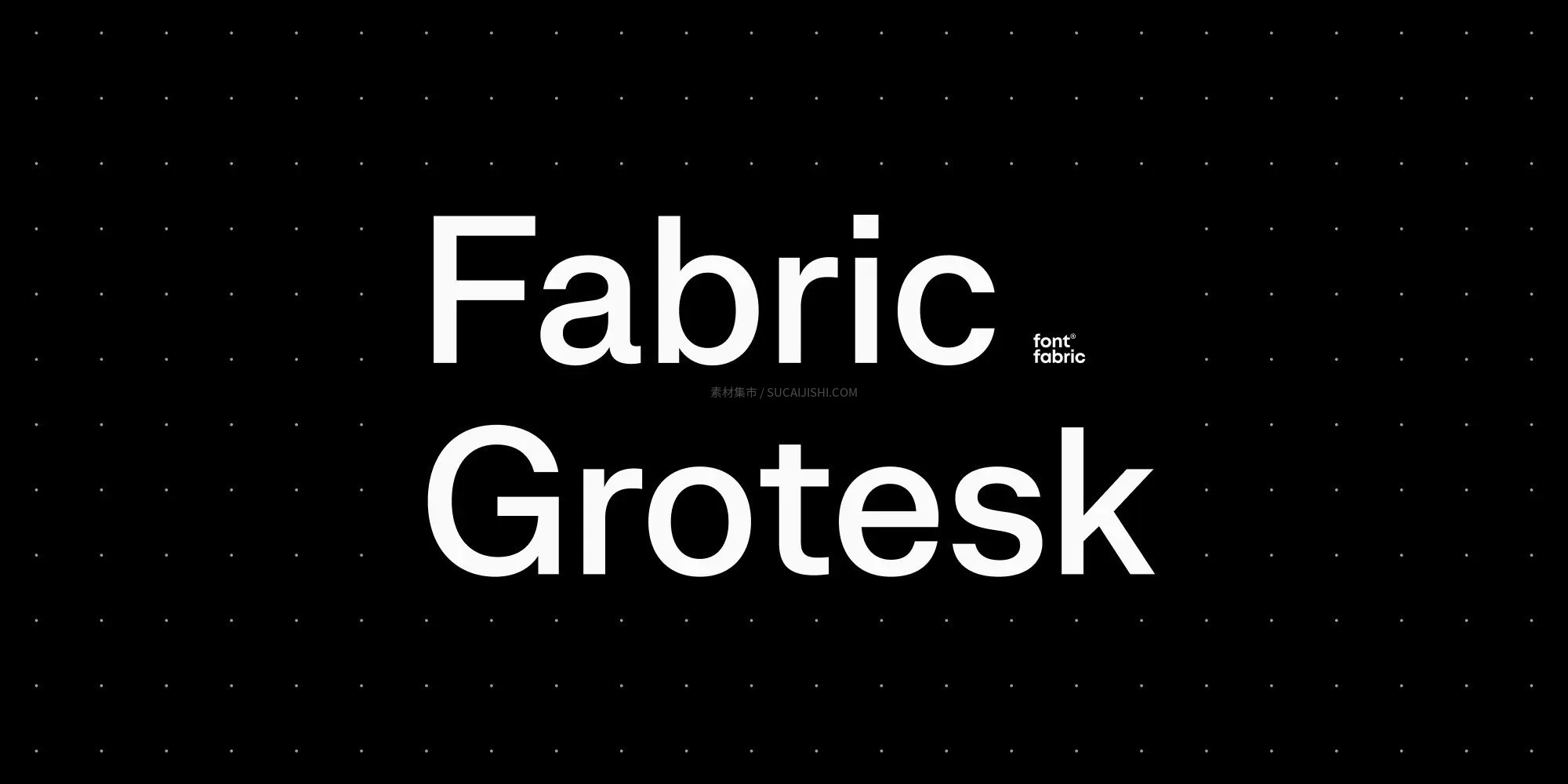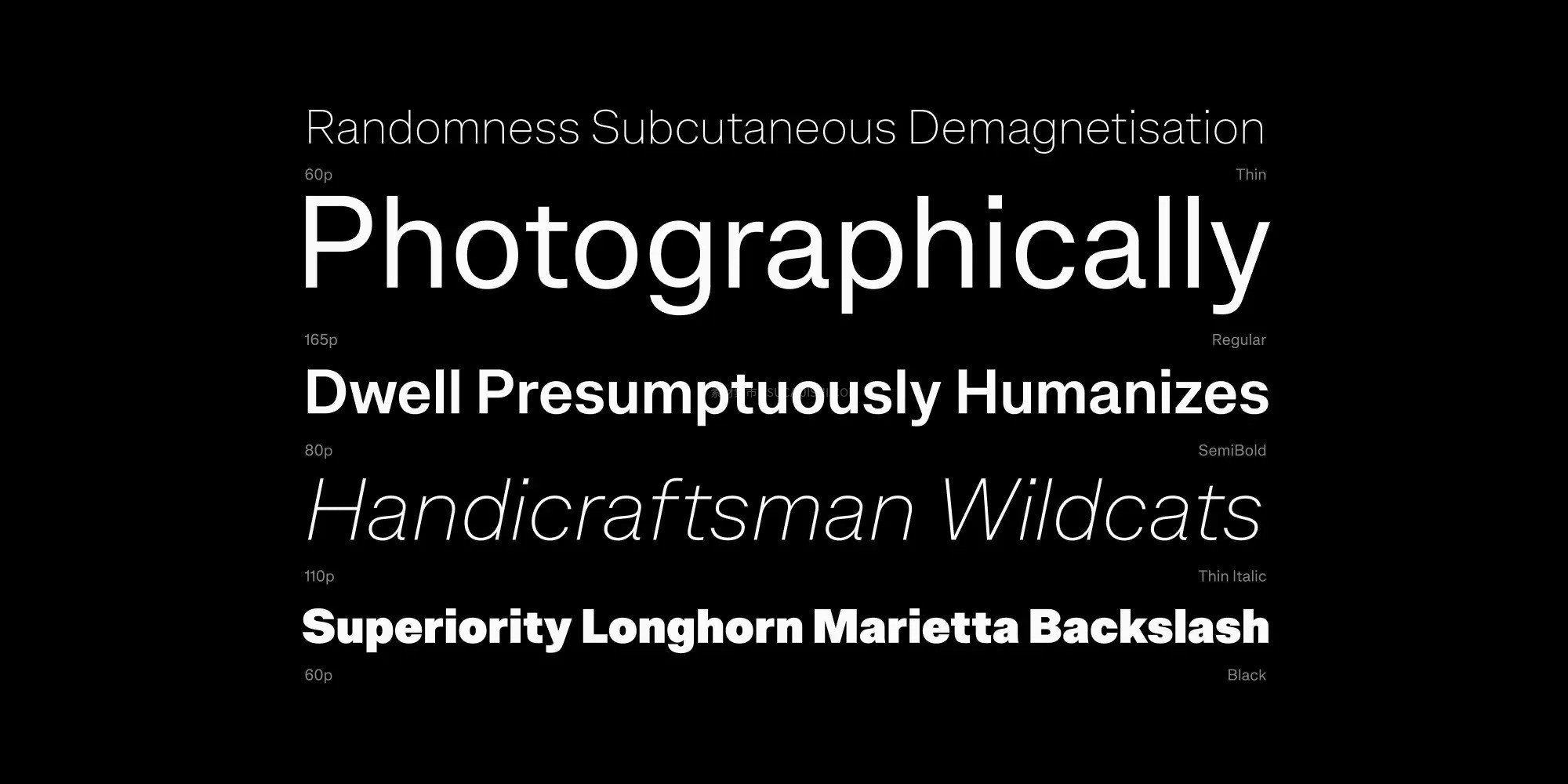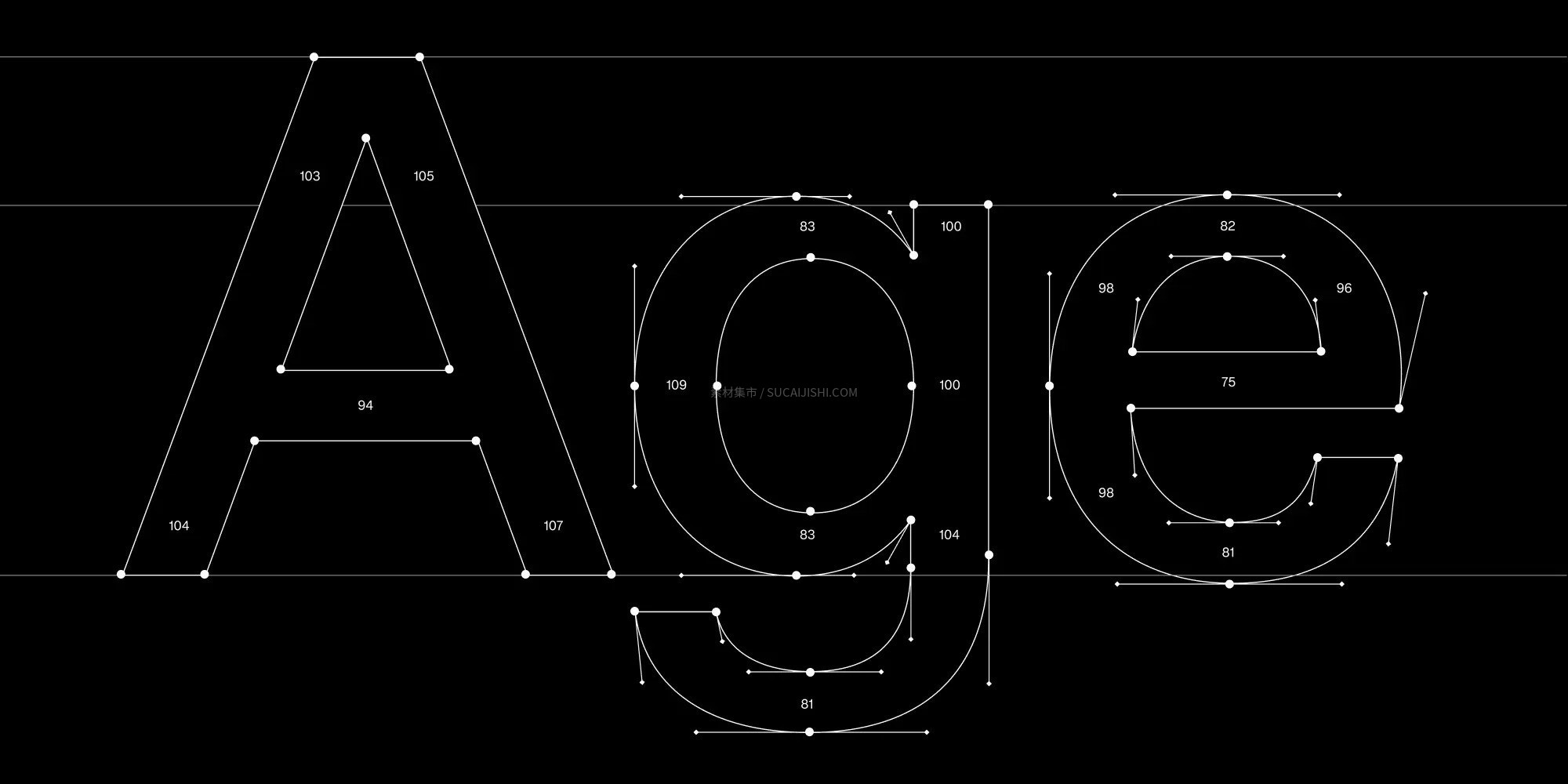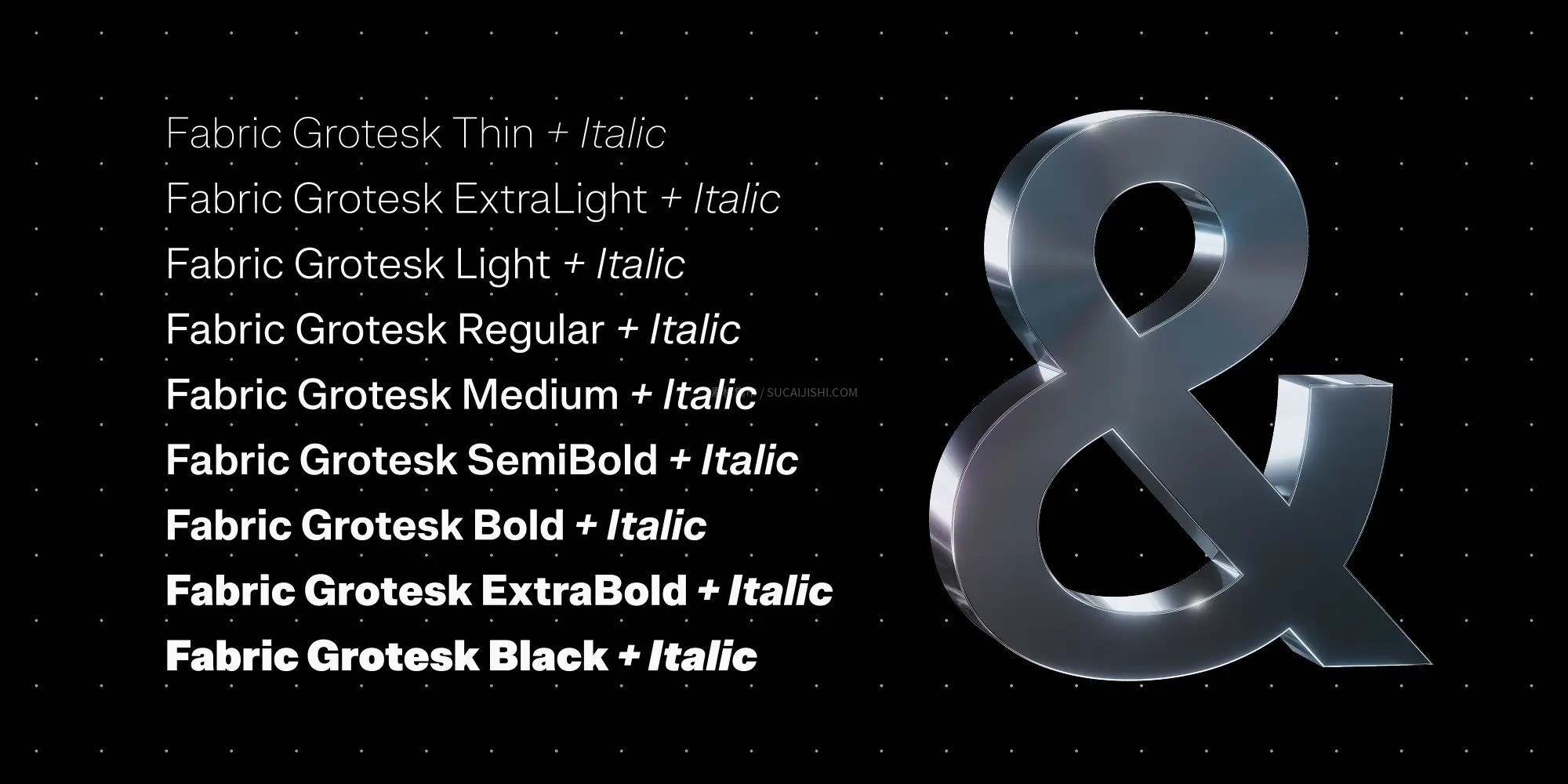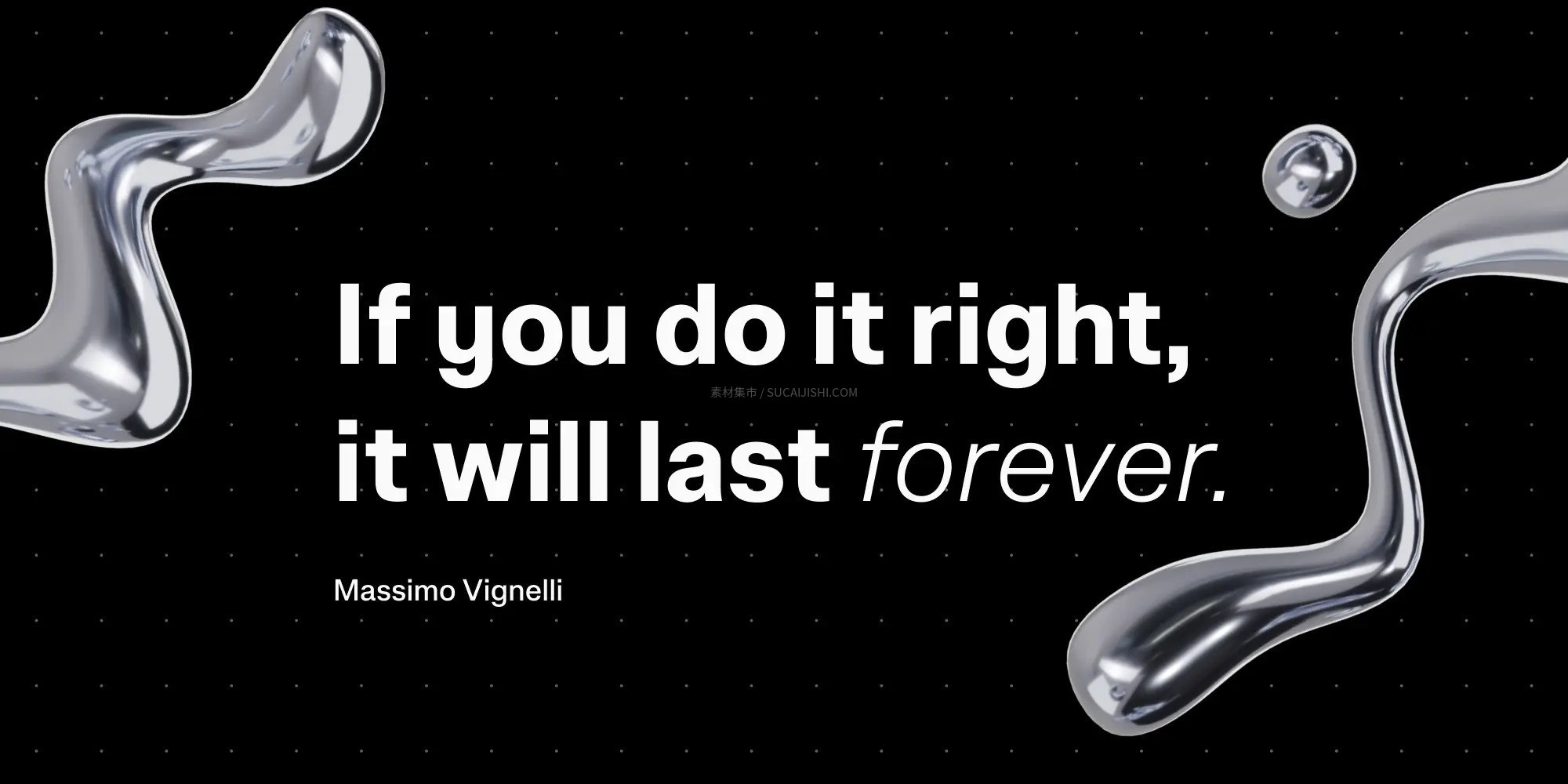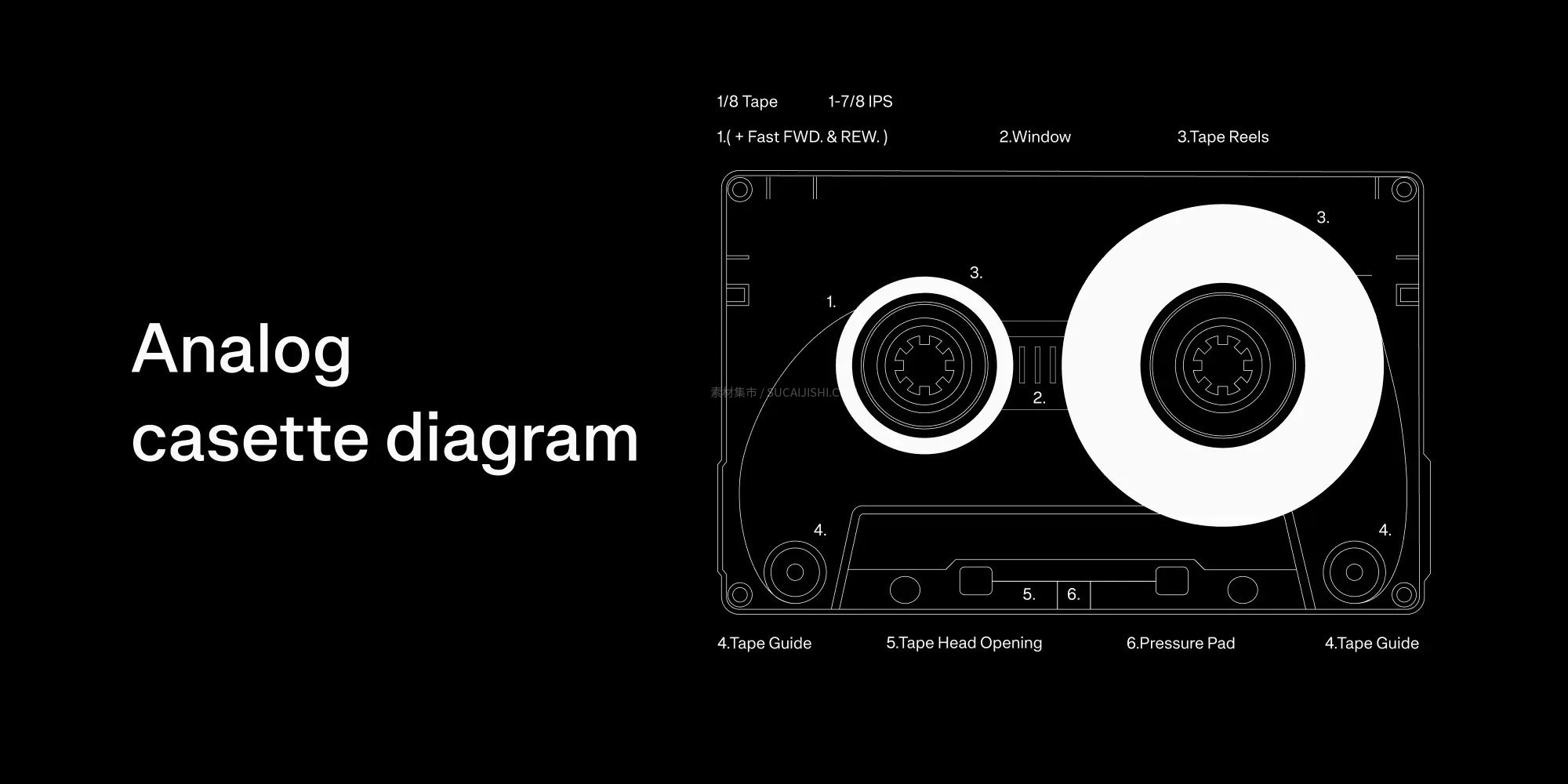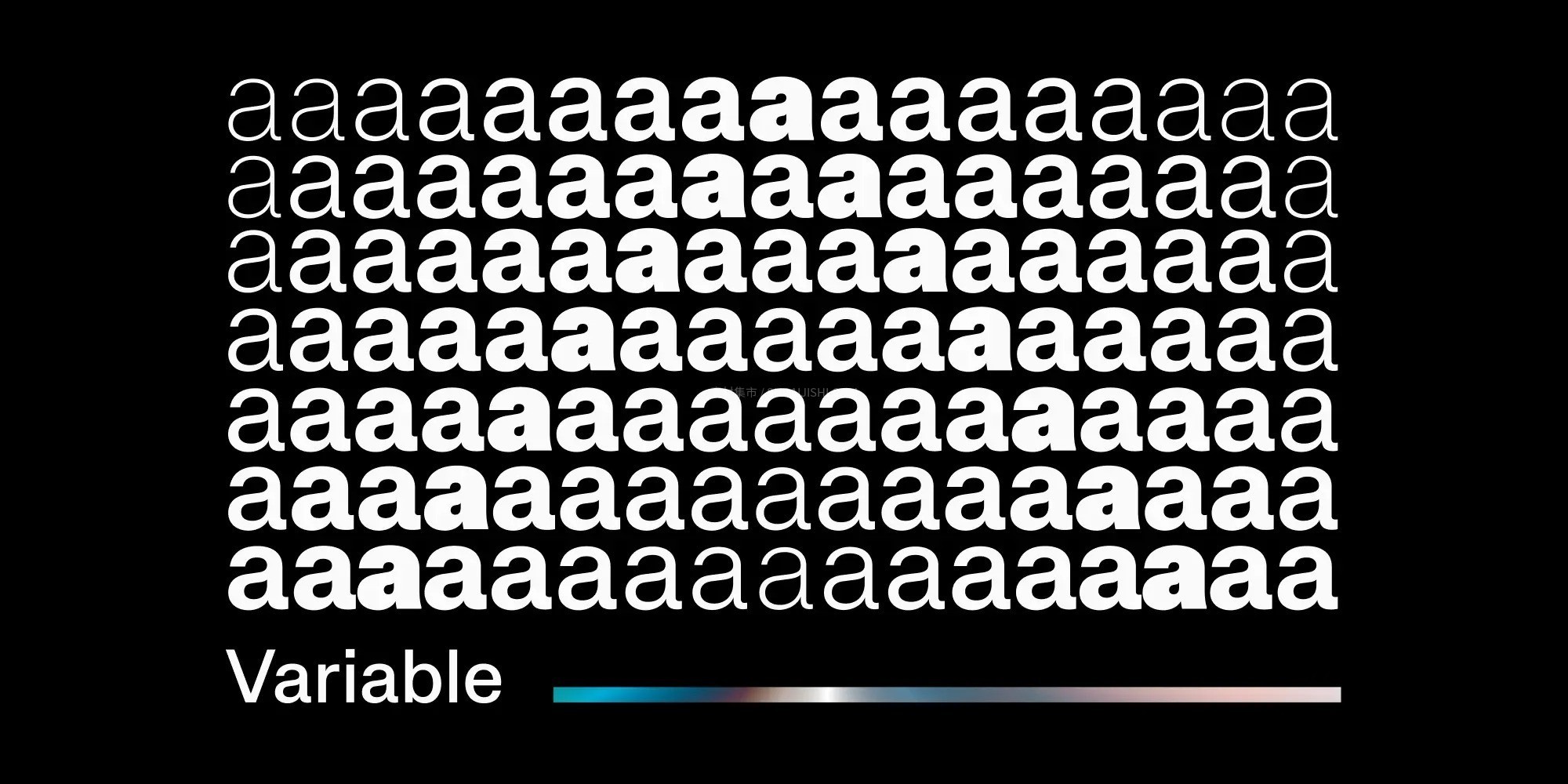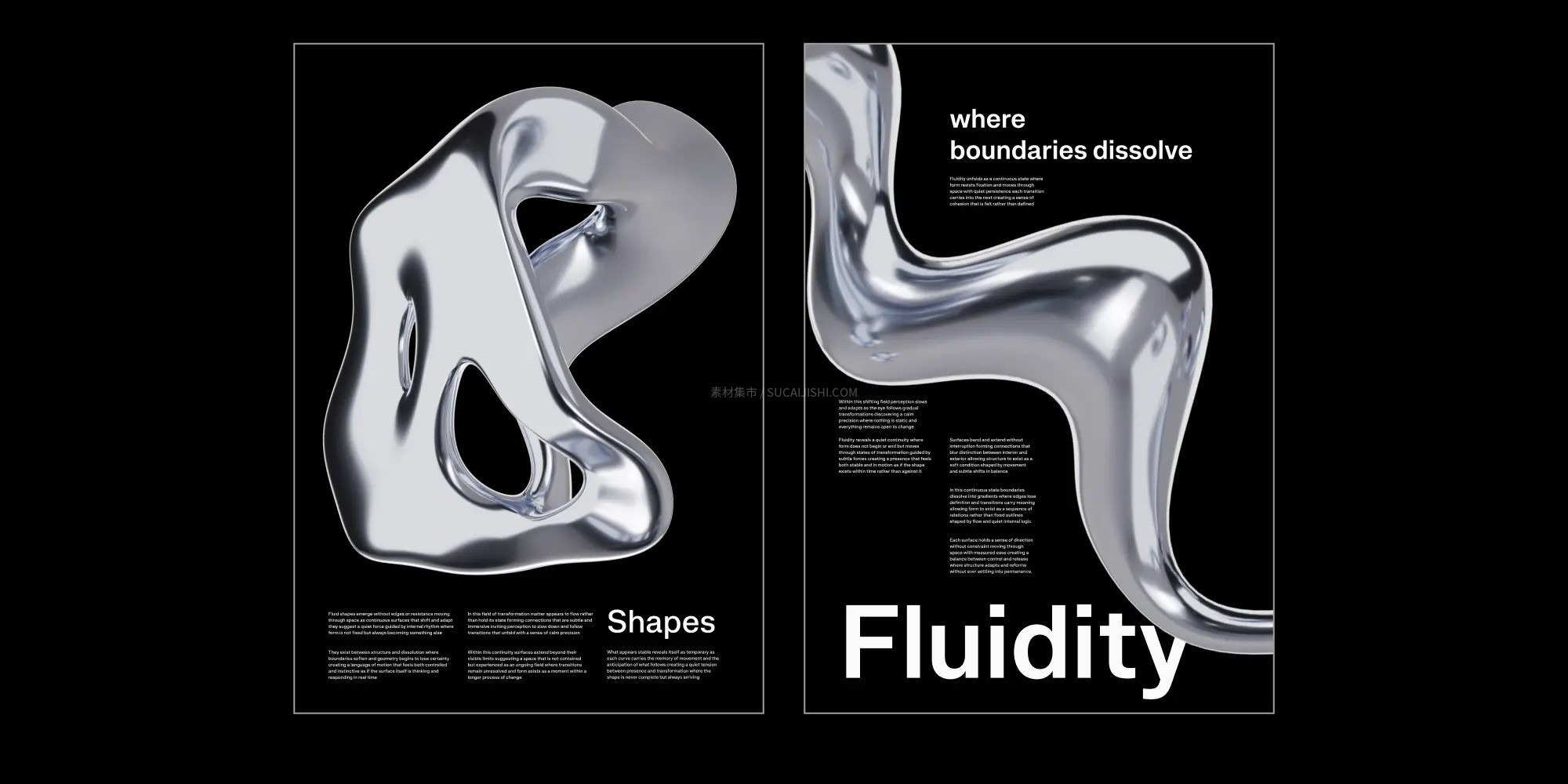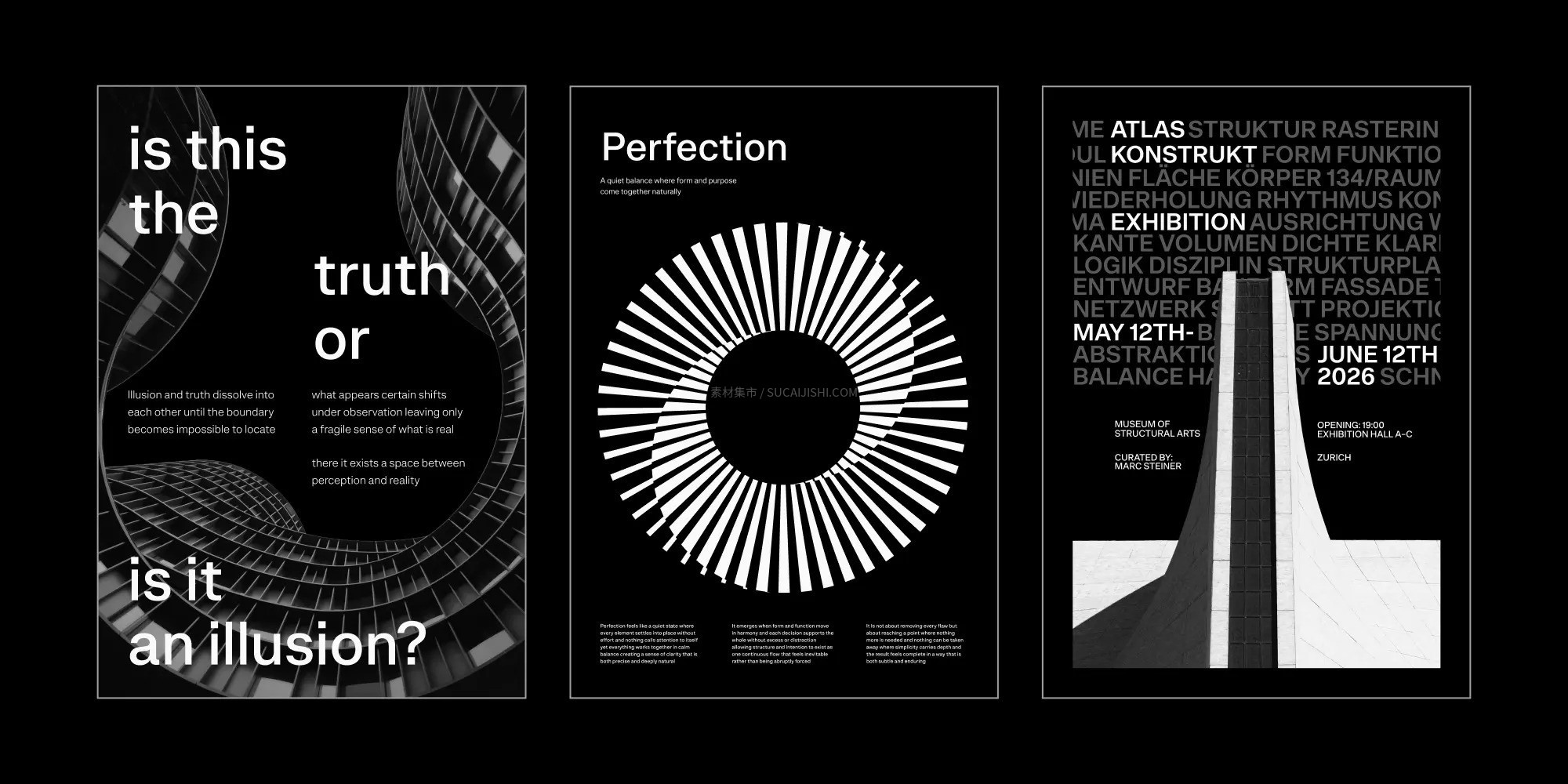
Fabric Grotesk 经典瑞士现代风无衬线字体
这款 Fabric Grotesk 绝对是你字库里超级百搭的新无衬线体 (Neo-Grotesk)!它致敬了世纪中期的经典瑞士设计风格,字形精致、曲线平衡,自带一种永恒又自信的高级感。全套包含 18 款静态样式和 1 款可变字体,排版正文时低调清晰,放大做标题又能展现出鲜明的个性细节。不仅支持丰富的 OpenType 功能和多语言,而且兼顾了美观与极强的实用性,不管做品牌还是做 UI,排版怎么搭都超级好用出片!